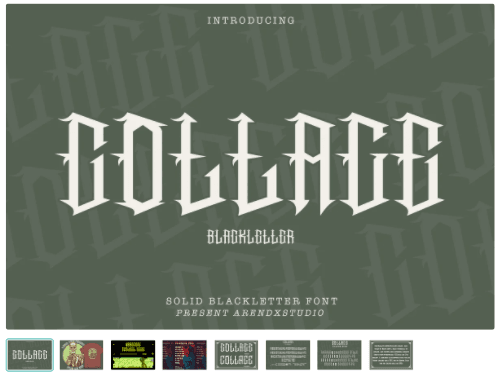
Cottage - Blackletter Font
Cottage - Blackletter Font содержит строчные и прописные буквы, символы, а также поддерживает многоязычность. В этом шрифте много лигатур. Cottage - Blackletter Font также включает лигатуры, стилистические варианты и многое другое. этот шрифт подходит для моды, брендинга, каталога и другого дизайна, который вы хотите.